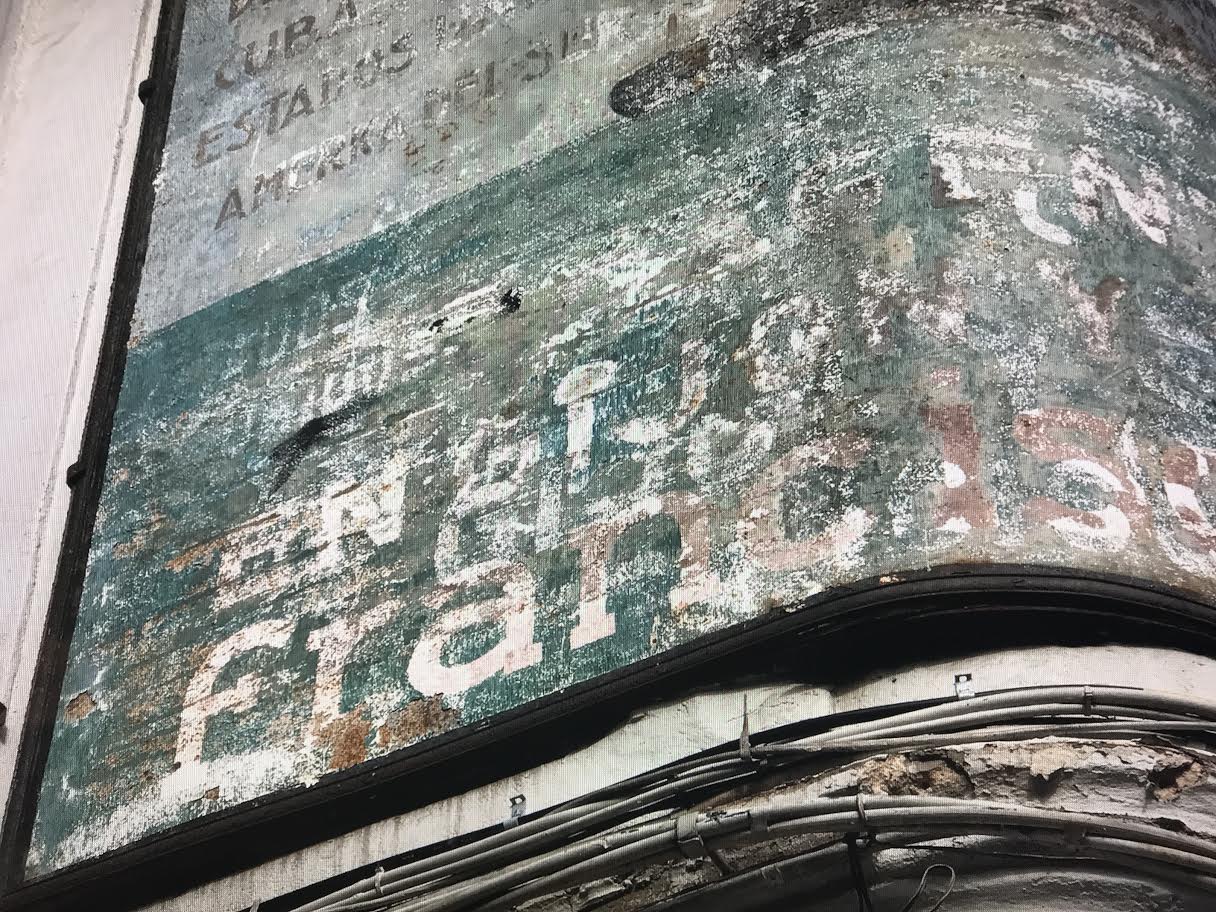
Pruebas de tipografia y diseños
Que el cartel de Hollan American Line se ha convertido en un icono, es indiscutible. Recientemente ha sufrido una nueva restauración de la mano de Grap SL y a pesar de lo dañado que estaba, le ha devuelto ese color y esos matices que le hacen único.
Entre otras curiosidades ha revelado que hasta el diseño final, pasó por distintas pruebas y rectificaciones tipográficas, lo cual da idea del trabajo artesanal «in situ» para su correcta percepción desde el suelo. Os dejamos unas fotosde detalle, cortesía de Grap SL, donde se ven esas pruebas y rectificaciones.